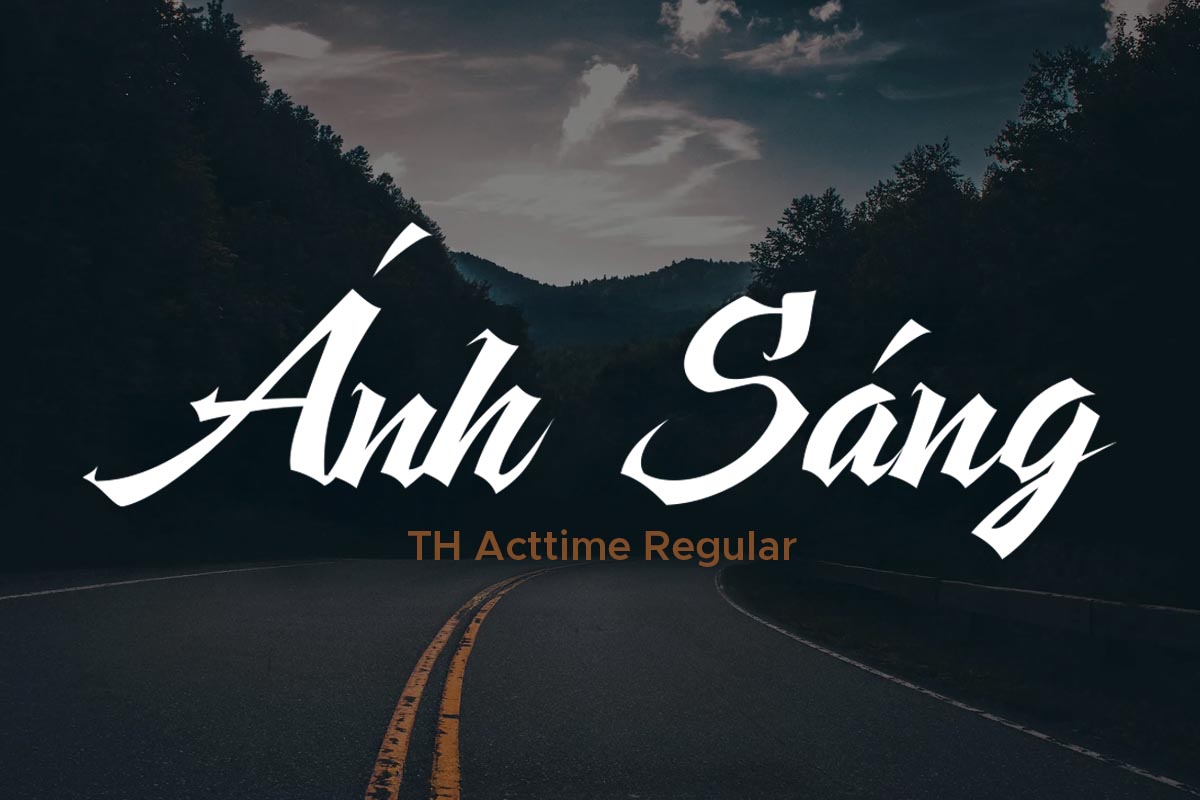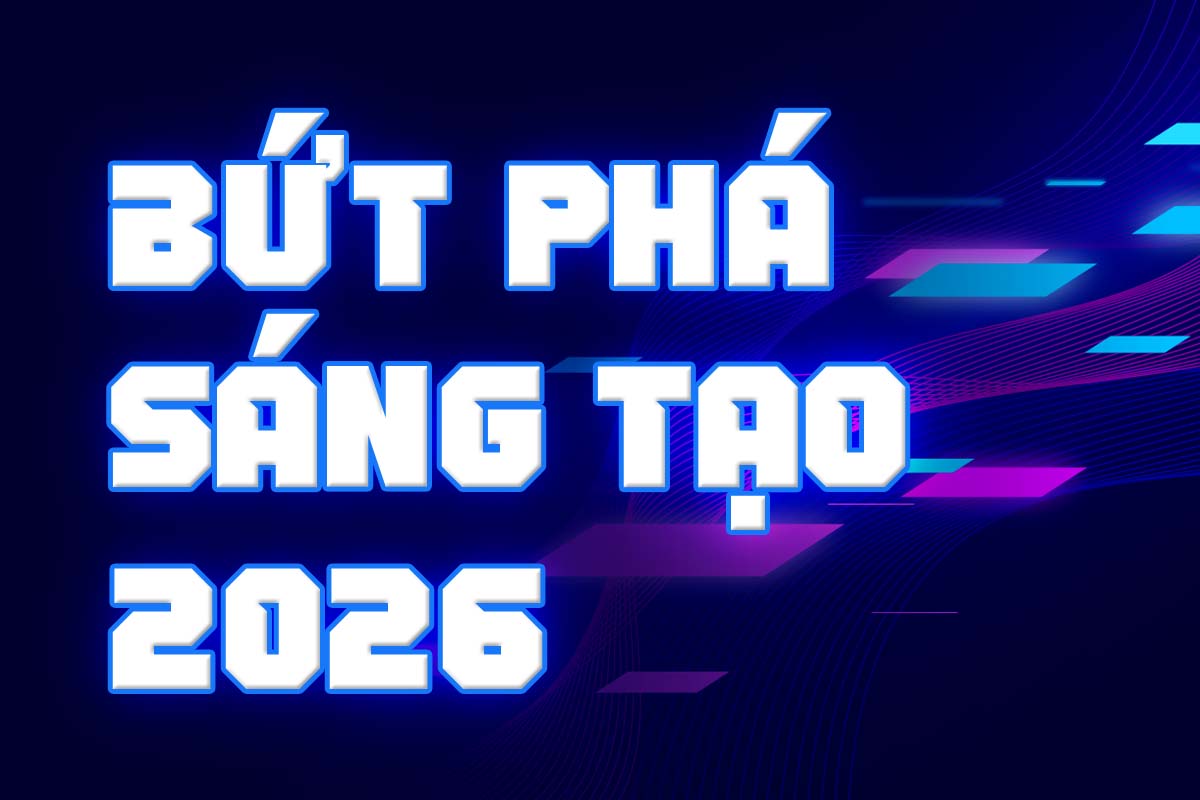
Top 30 font chữ đẹp cho thiết kế social media 2026
Gợi ý 30 font TH Việt hóa đẹp cho thiết kế social media 2026: Facebook, Instagram, TikTok, thumbnail, story, carousel và banner quảng cáo.
Social media là nơi người xem quyết định rất nhanh: dừng lại, lướt qua, bấm xem tiếp hay lưu bài. Vì vậy font chữ không chỉ là phần trang trí. Font quyết định tốc độ đọc, cảm giác thương hiệu và khả năng nổi bật của bài đăng trong một màn hình đầy nội dung cạnh tranh.
Với tiếng Việt, chọn font cho Facebook, Instagram, TikTok hay thumbnail còn khó hơn vì dấu phải hiển thị rõ. Một font đẹp nhưng dấu bị lệch, rơi, quá sát hoặc khó đọc sẽ làm bài đăng kém chuyên nghiệp. Danh sách dưới đây tập trung vào các font TH Việt hóa trên Fontdep.vn, có thể dùng cho tiêu đề, quote, cover video, carousel, story, banner sale và các chiến dịch thương mại.
Khi chọn font chữ social media, bạn nên nghĩ theo tình huống dùng: bài bán hàng cần font đậm và rõ, carousel kiến thức cần font dễ đọc, quote cần font có cảm xúc, còn TikTok cover hoặc thumbnail cần font đủ mạnh để nhìn được ở kích thước nhỏ. Một thư viện font tốt nên có đủ các nhóm này để thiết kế không bị một màu.
Tiêu chí chọn font chữ social media đẹp
Font social media tốt cần có độ đọc cao trên màn hình điện thoại. Người xem thường nhìn bài ở kích thước nhỏ, trong vài giây đầu, nên headline phải đủ rõ ngay cả khi ảnh bị nén hoặc nằm trong feed đông nội dung.
Tiêu chí thứ hai là hỗ trợ tiếng Việt đầy đủ. Hãy test các cụm như "ưu đãi", "khuyến mãi", "đặc biệt", "thương hiệu", "sản phẩm mới", "đăng ký ngay" trước khi dùng. Nếu dấu bị dính vào chữ hoặc mất cân bằng, font đó chỉ nên dùng rất hạn chế.
Tiêu chí thứ ba là đúng cá tính thương hiệu. Một font sport không nên dùng cho spa cao cấp; một font viết tay mảnh cũng không hợp thumbnail giảm giá cần va đập thị giác. Font đẹp nhất là font phục vụ đúng thông điệp.
Cách phối font cho Facebook, Instagram, TikTok và thumbnail
Với Facebook, bạn có thể dùng font headline đậm kết hợp font sans-serif dễ đọc cho mô tả ngắn. Các bài bán hàng, tuyển sinh, tuyển dụng hoặc sự kiện nên ưu tiên chữ rõ, khoảng cách thoáng và tương phản mạnh.
Với Instagram, font cần có gu thị giác hơn. Feed đẹp thường dùng serif sang, sans tối giản, script mềm hoặc vintage có kiểm soát. Tuy nhiên đừng dùng font trang trí cho toàn bộ caption trong ảnh; hãy để font trang trí làm điểm nhấn.
Với TikTok và thumbnail video, tiêu đề cần rất ngắn. Hãy chọn font display, condensed, sport hoặc brush, sau đó thêm viền, bóng đổ hoặc nền tương phản. Mục tiêu là đọc được trong chưa đầy một giây.
Top 30 font chữ đẹp cho thiết kế social media 2026
Danh sách dưới đây ưu tiên font TH Việt hóa có thể ứng dụng nhanh vào bài đăng mạng xã hội. Bạn có thể tải từng font, test thử bằng câu tiếng Việt thật của thương hiệu, sau đó lưu lại thành bộ font riêng cho từng nhóm nội dung.
1. TH Geardive
TH Geardive là font chữ thể thao mang phong cách tương lai, hợp thumbnail YouTube, poster workout, nội dung e-sport và các bài đăng cần cảm giác tốc độ. Khi dùng cho social media, hãy ưu tiên đặt font ở headline hoặc cụm nhấn chính, sau đó phối với một font sans-serif đơn giản cho phần mô tả nhỏ để tổng thể dễ đọc hơn.
2. TH Belly & Park
TH Belly & Park là font condensed hiện đại, tiết kiệm chiều ngang, rất hợp cover Reels, story sale, tiêu đề ngắn và các banner nhiều thông tin. Khi dùng cho social media, hãy ưu tiên đặt font ở headline hoặc cụm nhấn chính, sau đó phối với một font sans-serif đơn giản cho phần mô tả nhỏ để tổng thể dễ đọc hơn.
3. TH Giabe
TH Giabe là font sans serif display cá tính, hợp post thương hiệu trẻ, fashion, streetwear, poster sự kiện và những layout cần headline khỏe. Khi dùng cho social media, hãy ưu tiên đặt font ở headline hoặc cụm nhấn chính, sau đó phối với một font sans-serif đơn giản cho phần mô tả nhỏ để tổng thể dễ đọc hơn.
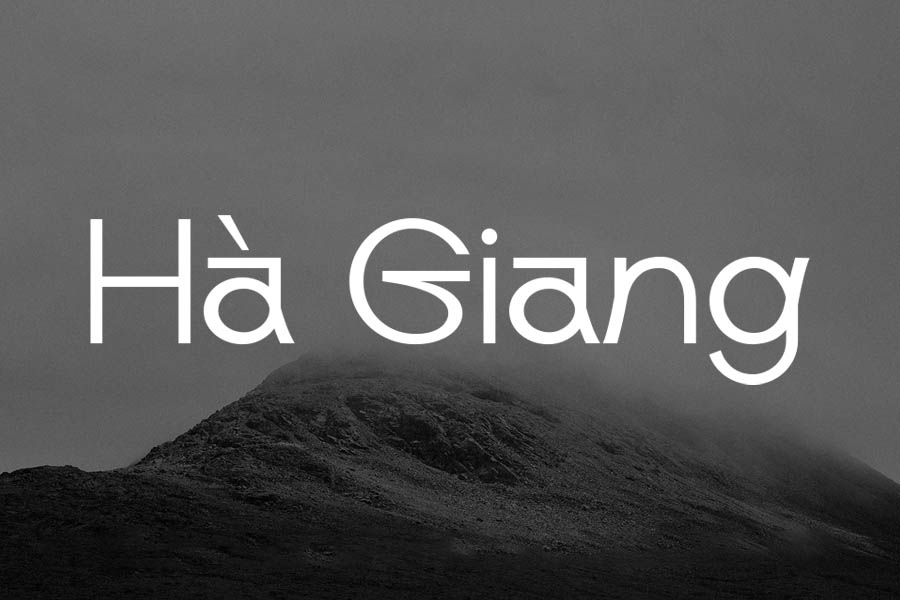
4. TH Algance
TH Algance là font sans serif tối giản, hợp carousel kiến thức, bài đăng thương hiệu cá nhân, infographic và nội dung cần đọc nhanh trên điện thoại. Khi dùng cho social media, hãy ưu tiên đặt font ở headline hoặc cụm nhấn chính, sau đó phối với một font sans-serif đơn giản cho phần mô tả nhỏ để tổng thể dễ đọc hơn.
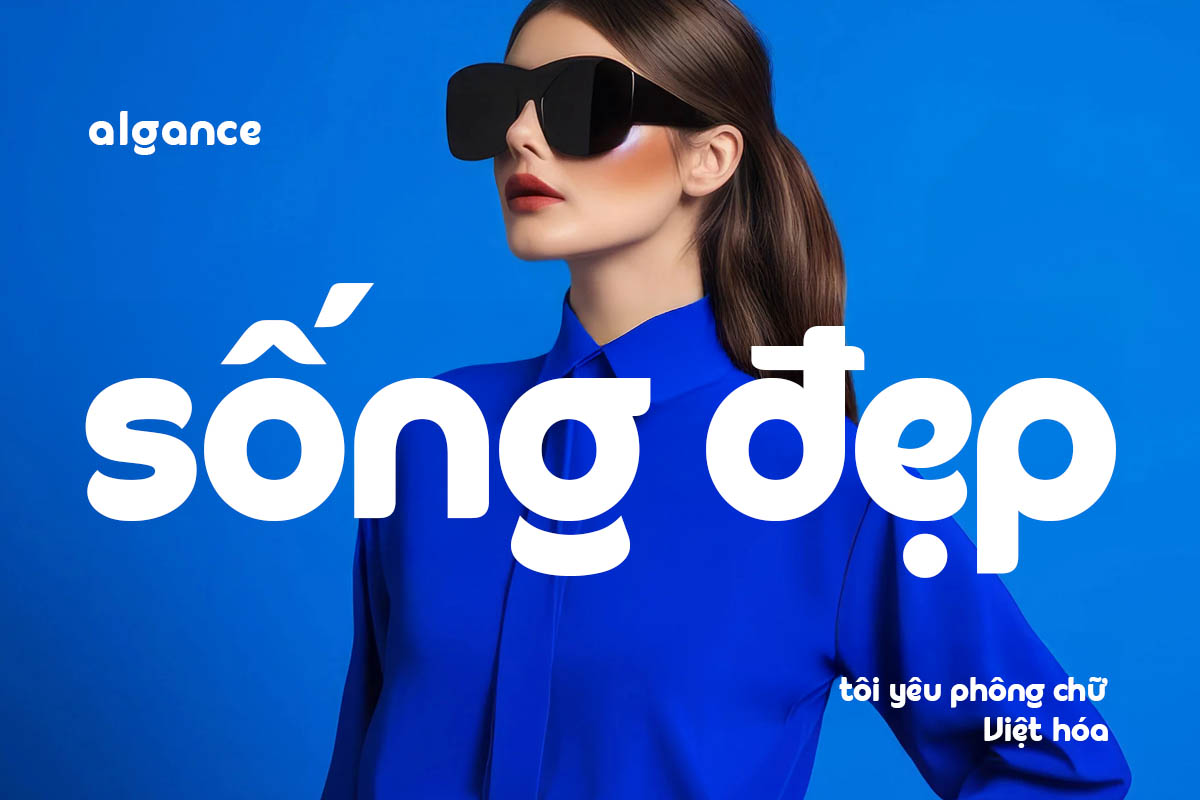
5. TH Axiome
TH Axiome là font công nghệ hiện đại, phù hợp TikTok cover, bài đăng startup, AI, phần mềm, gadget và những nội dung cần cảm giác tương lai. Khi dùng cho social media, hãy ưu tiên đặt font ở headline hoặc cụm nhấn chính, sau đó phối với một font sans-serif đơn giản cho phần mô tả nhỏ để tổng thể dễ đọc hơn.
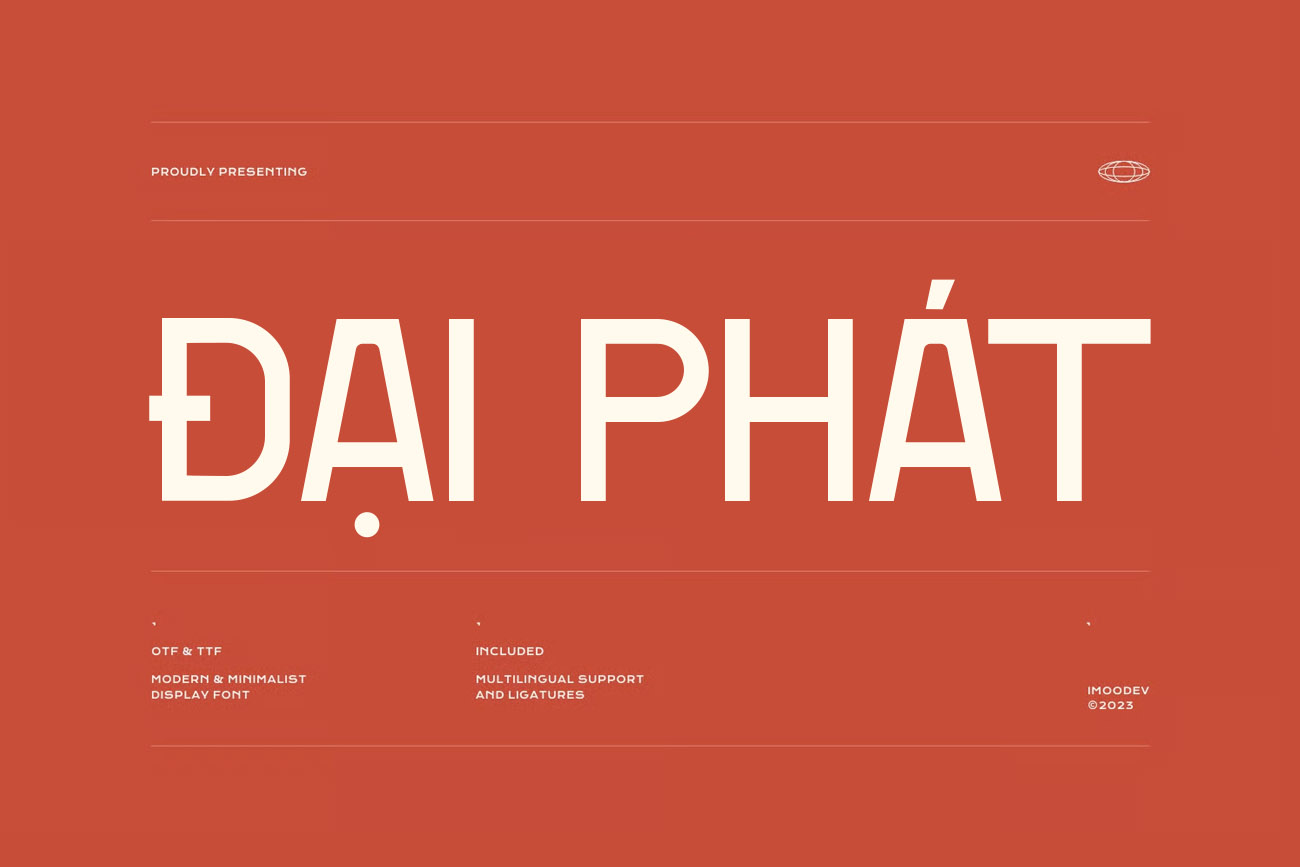
6. TH Seona Display
TH Seona Display là font công nghệ có tạo hình rõ, hợp landing social, banner khóa học công nghệ, cover livestream và poster sản phẩm số. Khi dùng cho social media, hãy ưu tiên đặt font ở headline hoặc cụm nhấn chính, sau đó phối với một font sans-serif đơn giản cho phần mô tả nhỏ để tổng thể dễ đọc hơn.
Một mẹo nhỏ là tạo sẵn 3 bộ font: bộ bán hàng, bộ nội dung kiến thức và bộ giải trí. Khi có lịch đăng dày, bạn chỉ cần chọn đúng bộ thay vì tìm font từ đầu. Cách này giúp fanpage, kênh TikTok hoặc Instagram giữ được nhận diện ổn định hơn.
Một font chữ social media tốt cần nổi bật, dễ đọc, đúng cảm xúc và hỗ trợ tiếng Việt ổn định. Bộ 30 font TH Việt hóa ở trên có thể giúp bạn xây dựng thư viện font đa dạng cho Facebook, Instagram, TikTok, thumbnail và story trong năm 2026. Hãy tải font phù hợp, test với nội dung thật, rồi lưu lại thành bộ nhận diện chữ riêng cho từng dạng bài.